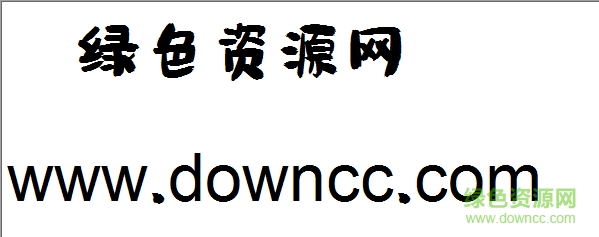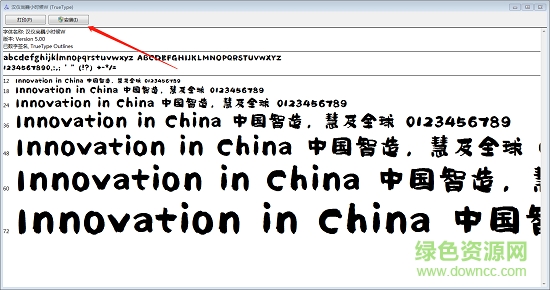
漢儀尚巍小時(shí)候字體素材
漢儀尚巍小時(shí)候字體是由漢儀開(kāi)發(fā)的一款非常簡(jiǎn)單的手寫(xiě)字體,簡(jiǎn)單干凈的字體筆鋒,支持幾種不同的漢字以及其他符號(hào),帶給用戶(hù)一種清新的感覺(jué),喜歡的用戶(hù)快來(lái)綠色資源網(wǎng)下載吧!
漢儀尚巍小時(shí)候字體簡(jiǎn)介:
漢儀尚巍小時(shí)候字體是一款由漢儀字體官網(wǎng)提供的中文簡(jiǎn)體手寫(xiě)字體,,能夠支持中文簡(jiǎn)體、拼音字母、數(shù)字符號(hào)等輸出格式,比較適合應(yīng)用到標(biāo)志、廣告、游戲、動(dòng)漫、影視中使用。
漢儀尚巍小時(shí)候字體特色:
-擁有簡(jiǎn)潔整齊的字體外觀,較粗的字體筆畫(huà)結(jié)構(gòu),整體看起來(lái)就像小時(shí)候?qū)懙臐h字一樣
-適用面廣,具有自己獨(dú)特的特色